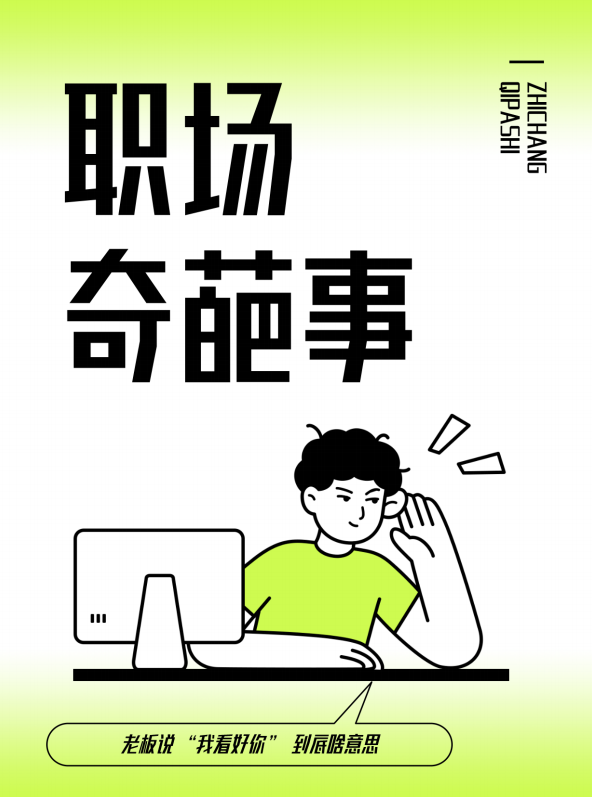
高手庆科竞速体 大黑
Master-ZqkjingsuGB Bold
字型瘦长工整,布白均匀,中宫紧凑,重心平稳。字体采用直线设计,横竖笔画视觉等粗,“钩”笔画采用去钩后笔画末端往内部加斜的处理方式。主次笔画的调整使内部留白均匀。笔画的起笔跟收笔处采用平切的方式,整体简洁工整。这款家族字体总共包含4个字重,适用标题和正文,实现由细到粗的平滑过渡,具有良好的视觉表现与阅读体验,可以适配多种风格与样式的排版。